Tải 17 font chữ wedding Việt hóa đẹp nhất 2025 – mềm mại, sang trọng, tương thích Canva, đầy đủ dấu tiếng Việt, lý tưởng cho thiệp cưới.
Trong thiết kế thiệp cưới, font chữ đóng vai trò không thể thiếu trong việc truyền tải cảm xúc và cá tính của cô dâu chú rể. Một kiểu chữ phù hợp sẽ giúp tấm thiệp trở nên sang trọng, lãng mạn và để lại ấn tượng sâu sắc.
Tại Fontdep.vn, chúng tôi đã tuyển chọn kỹ lưỡng top 17 font chữ wedding Việt hóa đẹp nhất năm 2025, không chỉ mang đến trải nghiệm thiết kế tối ưu mà còn đảm bảo đầy đủ dấu tiếng Việt, tương thích với Canva, Photoshop và các phần mềm thiết kế phổ biến. Danh sách đi kèm link tải, hướng dẫn cài đặt và gợi ý sử dụng thực tế giúp bạn dễ dàng áp dụng ngay vào dự án của mình.
Font Wedding là gì? Vì sao nên chọn font Việt hóa?
Font wedding là những kiểu chữ được thiết kế chuyên biệt cho thiệp mời, bảng tên, backdrop tiệc cưới... Thông thường, các font này có nét viết tay mềm mại, chữ ký tinh tế, hoặc serif thanh lịch, tạo cảm giác trang trọng, yêu thương và riêng biệt cho buổi lễ.
Font wedding Việt hóa là những bộ font đã được bổ sung đầy đủ dấu tiếng Việt như ă, â, ê, đ… giúp hiển thị chính xác khi in ấn hoặc thiết kế. Đây là lựa chọn lý tưởng cho các thiết kế hướng đến thị trường Việt Nam.
Tiêu chí chọn font wedding đẹp, dễ dùng cho năm 2025
Khi lựa chọn font chữ cho thiệp cưới, bạn nên cân nhắc các yếu tố sau:
- Phong cách thiết kế: Script, calligraphy, signature hoặc serif cổ điển.
- Cảm xúc truyền tải: Sang trọng, hiện đại, cổ điển hay tối giản.
- Hỗ trợ tiếng Việt: Đầy đủ dấu, chuẩn Unicode, dễ dùng trên các phần mềm thiết kế.
- Tính tương thích: Font nên hoạt động tốt trên Canva, Word, AI, PS...
- Bản quyền rõ ràng: Ưu tiên font miễn phí hoặc có license minh bạch.
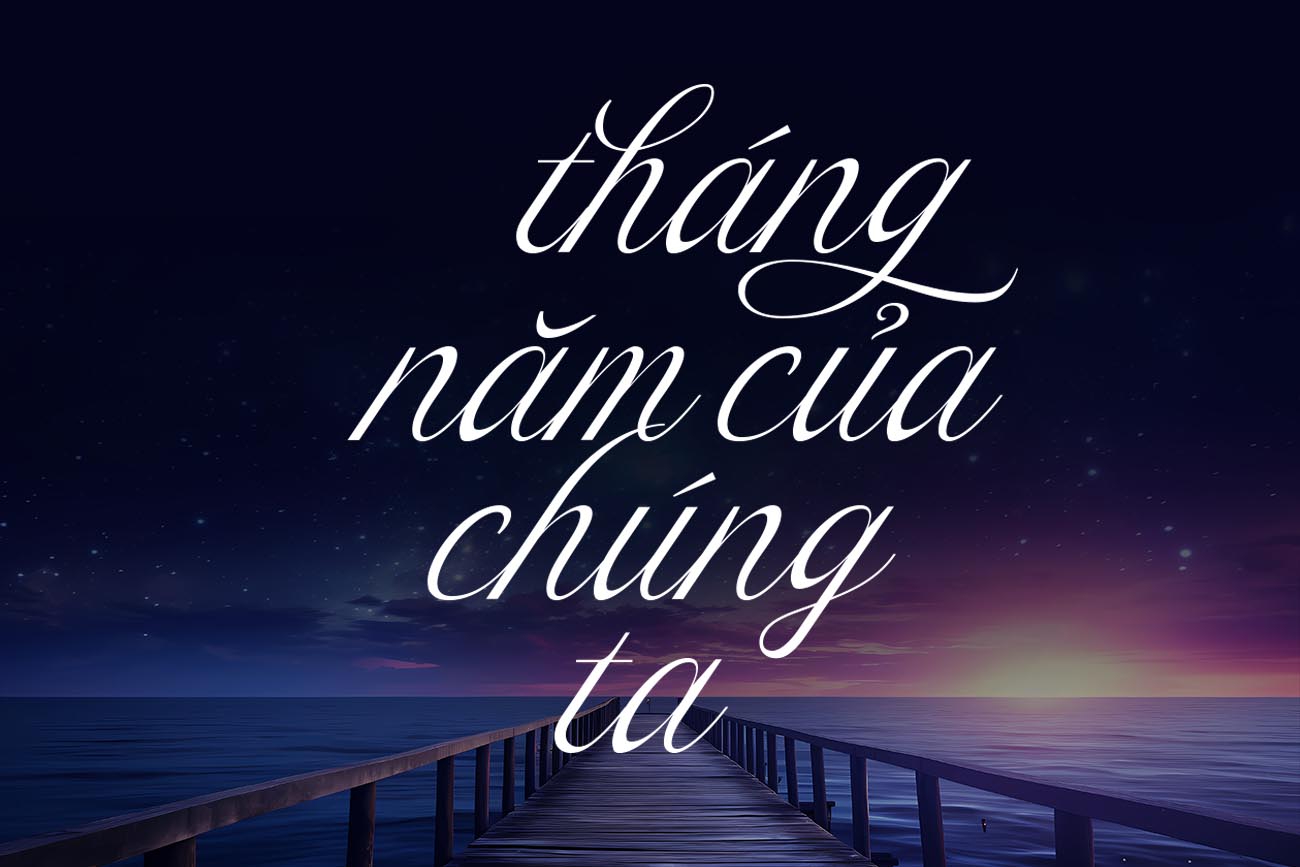
Bộ sưu tập 17 font wedding Việt hóa đẹp nhất 2025
Danh sách dưới đây được sắp xếp dựa theo mức độ phổ biến, tính ứng dụng và phong cách thiết kế. Mỗi font đều hỗ trợ đầy đủ tiếng Việt, dễ cài đặt và sử dụng ngay:
NVN Motherland Signature – Font cưới chữ ký Việt hóa tinh tế
Là một kiểu font viết tay mô phỏng chữ ký bằng bút lông, mang đậm chất hiện đại pha chút cổ điển. Đường nét uyển chuyển, tinh tế, có độ nhấn nhá rõ ràng, rất phù hợp dùng làm tên cô dâu chú rể trên thiệp cưới, tiêu đề hoặc logo cá nhân cho studio chụp ảnh cưới.
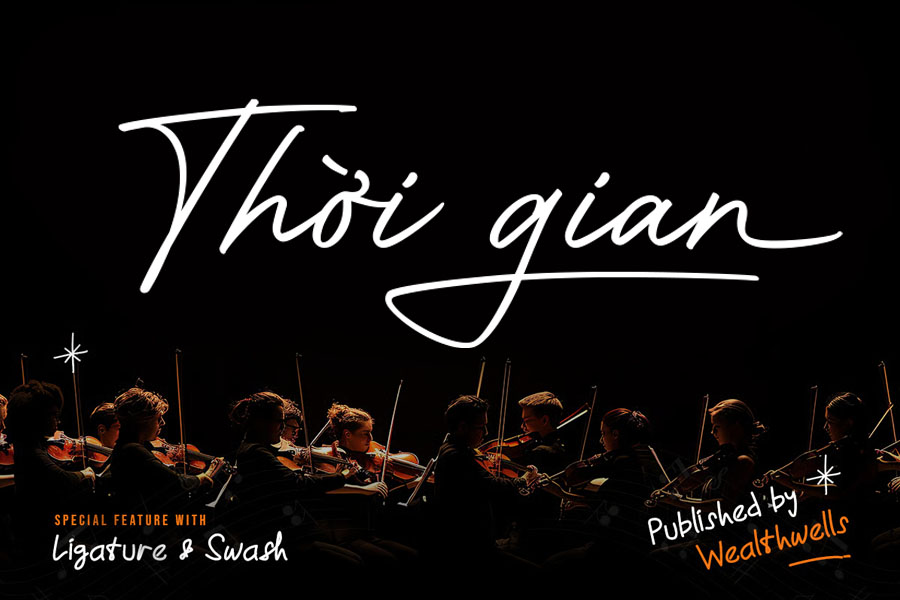
SVN Rosellinda Alyamore – Font wedding viết tay nhẹ nhàng
Rosellinda Alyamore là một font chữ viết tay mang phong cách chữ ký thanh thoát, mềm mại và đầy chất thơ. Lấy cảm hứng từ nét chữ mực tay truyền thống, font sở hữu độ nghiêng nhẹ cùng đường dẫn tự nhiên, tạo cảm giác bay bổng nhưng vẫn dễ đọc. Font chữ cực kỳ lý tưởng để in tên cô dâu hoặc phần trích dẫn nhẹ nhàng trong thiệp mời cưới hiện đại.
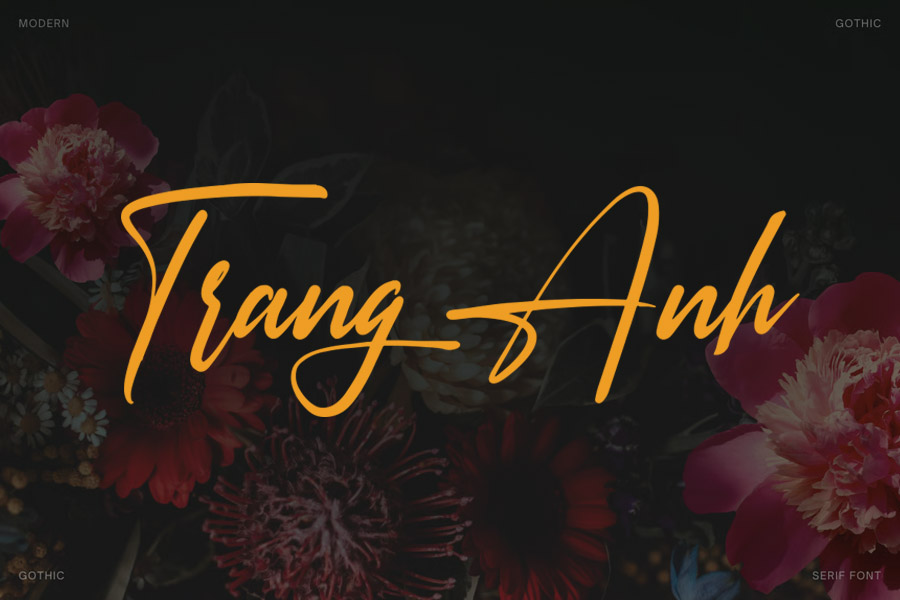
Qalisha Signature – Font cưới Việt hóa thanh lịch, cảm xúc
Bộ đôi font serif và chữ ký hoàn hảo cho thiệp cưới sang trọng. Kiểu chữ thanh mảnh, đầy cảm xúc, thích hợp làm tên cô dâu chú rể hoặc phần mở đầu thiệp cưới mang phong cách cổ điển, hoài niệm.
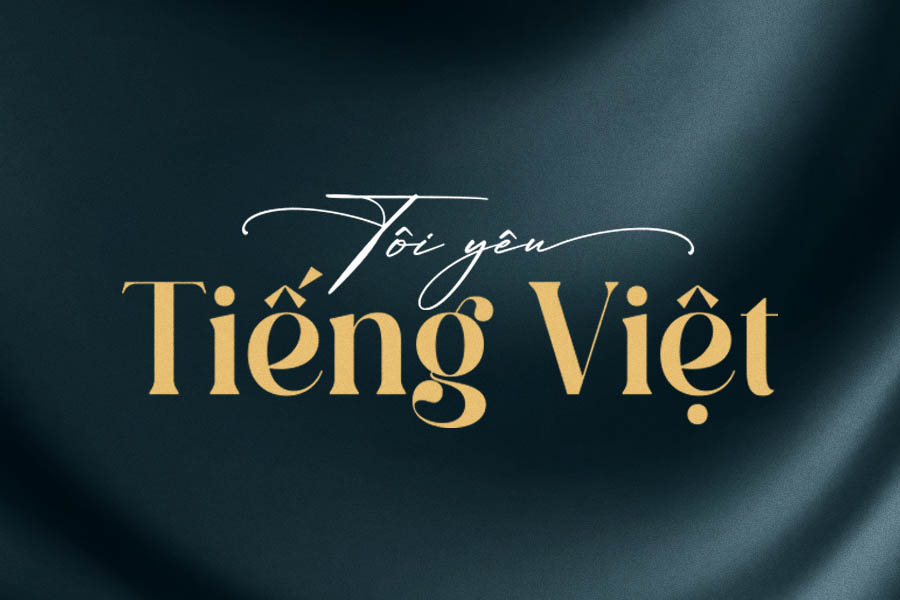
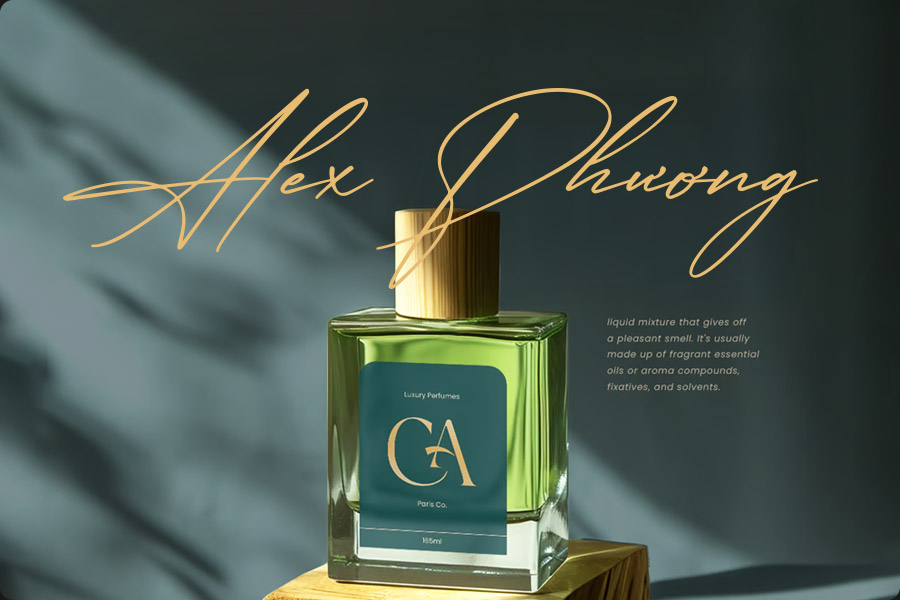
TH Bengoda – Font chữ ký cưới mềm mại, Việt hóa
Font chữ ký Việt hóa mềm mại, nhẹ nhàng và uyển chuyển. Đường nét cong uyển chuyển rất phù hợp làm dòng chữ trung tâm cho thiệp cưới tối giản, phong cách Hàn Quốc hoặc boho nhẹ nhàng.
- Tác giả gốc: Rantautype Studio
- Việt hóa bởi: Phạm Sơn - Admin S99, Fontdep.vn
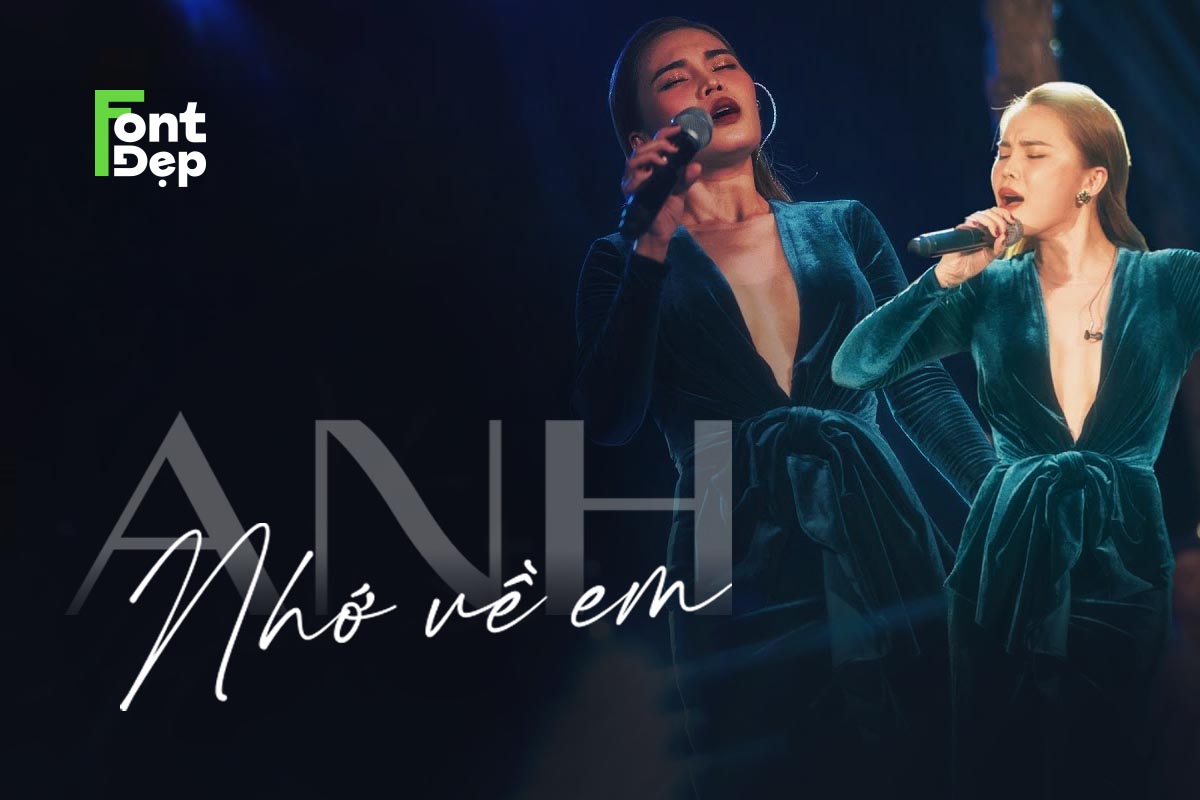
SVN Nautica – Font viết tay cao cấp cho thiệp cưới
Font viết tay sang trọng, nét thanh mạnh tạo nên cảm giác cao cấp và chuyên nghiệp. Rất phù hợp cho tên thương hiệu studio cưới, tiêu đề trong thiệp hoặc in trên bao thư thiệp mời.
- Tác giả gốc: STYLEno.1
- Việt hóa bởi: STYLEno.1
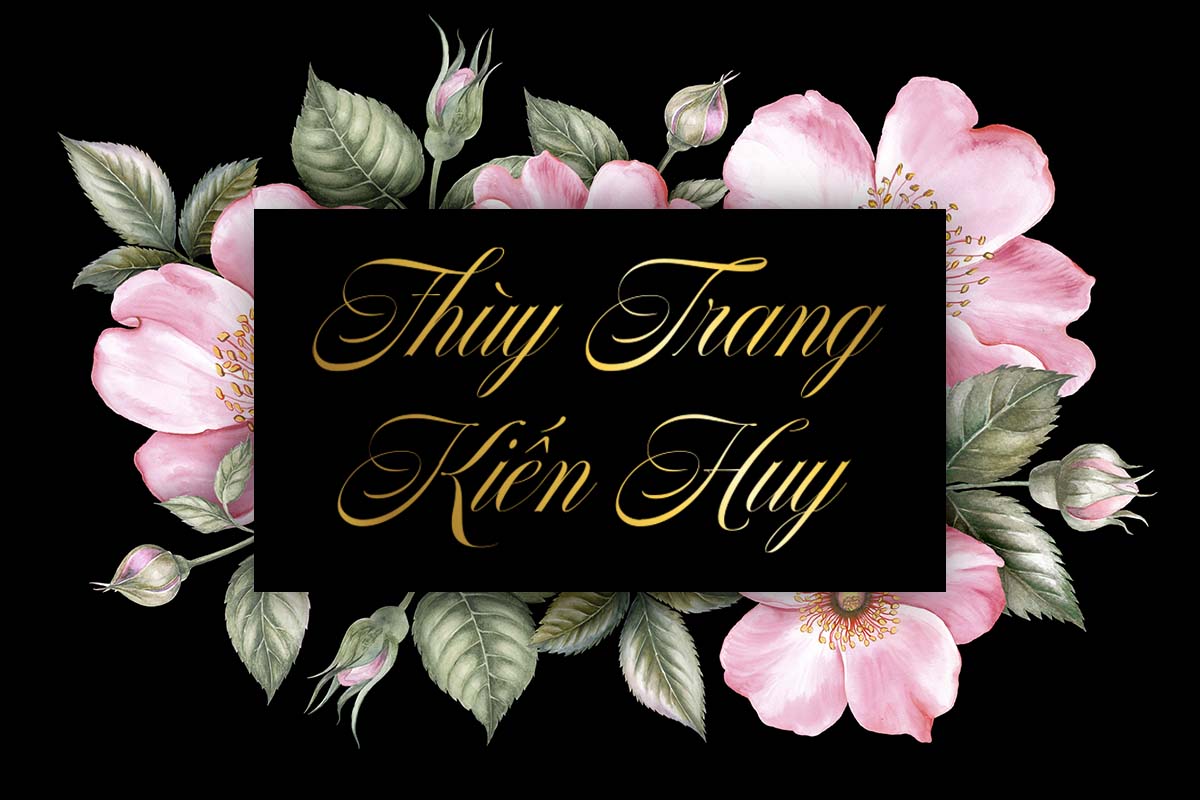
TH Milyah – Font chữ ký cưới mảnh mai, hiện đại
Font chữ ký cá nhân với nét mảnh, sang trọng và hiện đại. Kiểu chữ phù hợp để in tên cô dâu chú rể trên thiệp cưới phong cách tối giản hoặc dùng trong thiết kế logo cưới, phong bì và bảng hiệu cưới.
- Tác giả gốc: Alit Design (thiết kế bởi Dwi Putra Yoga)
- Việt hóa bởi: Phạm Sơn - Admin S99, Fontdep.vn
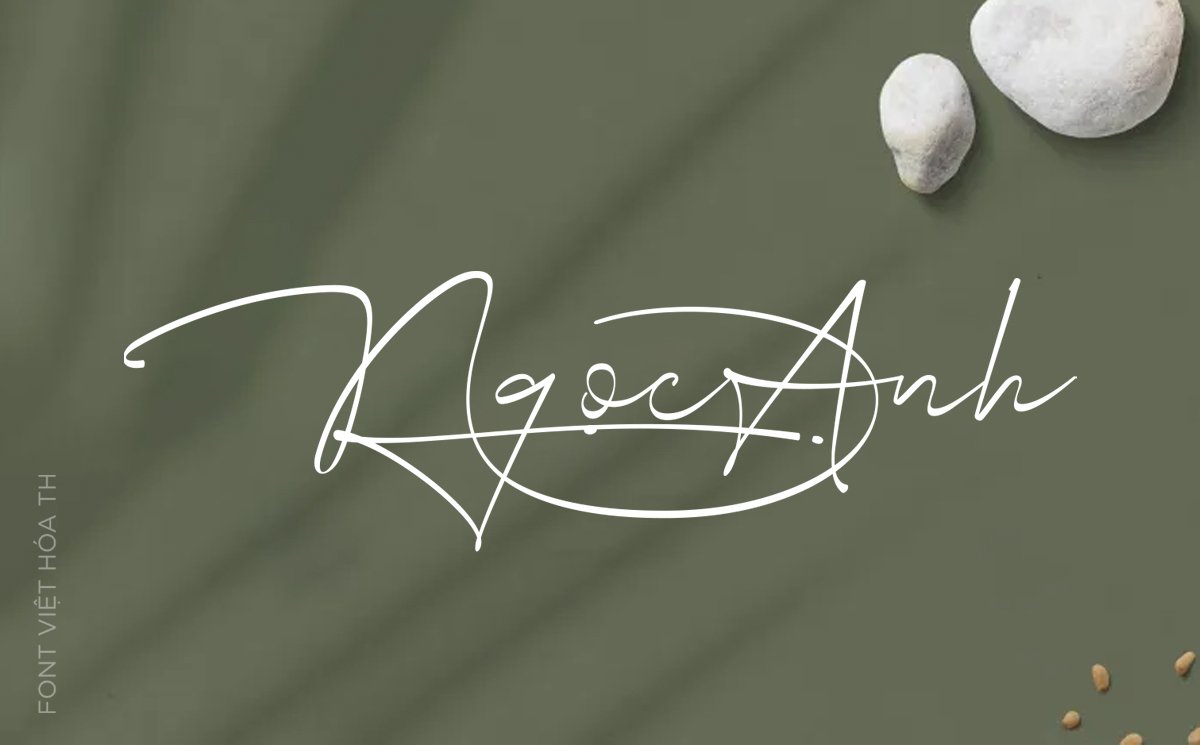
TH Maistoray – Font cưới viết tay nghiêng nhẹ, bay bổng
Font chữ viết tay hiện đại, nghiêng nhẹ và mềm mại, tạo cảm giác bay bổng và tình cảm. Phù hợp với thiệp cưới phong cách nghệ thuật, nhẹ nhàng hoặc retro.
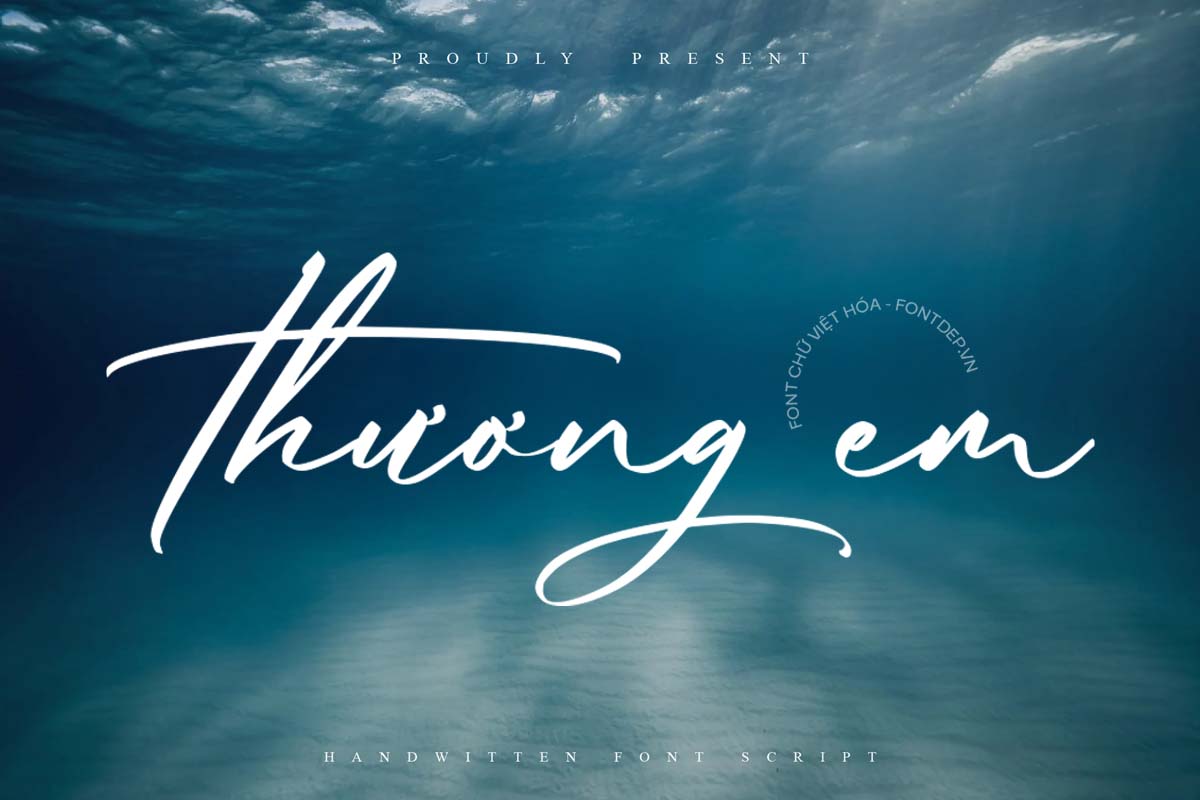
TH Nice Memory – Font wedding retro hoài cổ, Việt hóa
Font chữ chính là linh hồn của thiệp cưới. Một font wedding Việt hóa không chỉ giúp thiết kế trở nên đẹp mắt mà còn thể hiện cá tính, cảm xúc và sự đồng điệu trong ngày trọng đại. Dù bạn là designer chuyên nghiệp hay chỉ mới bắt đầu thiết kế cho lễ cưới của chính mình, bộ font dưới đây sẽ là công cụ tuyệt vời để bắt đầu.